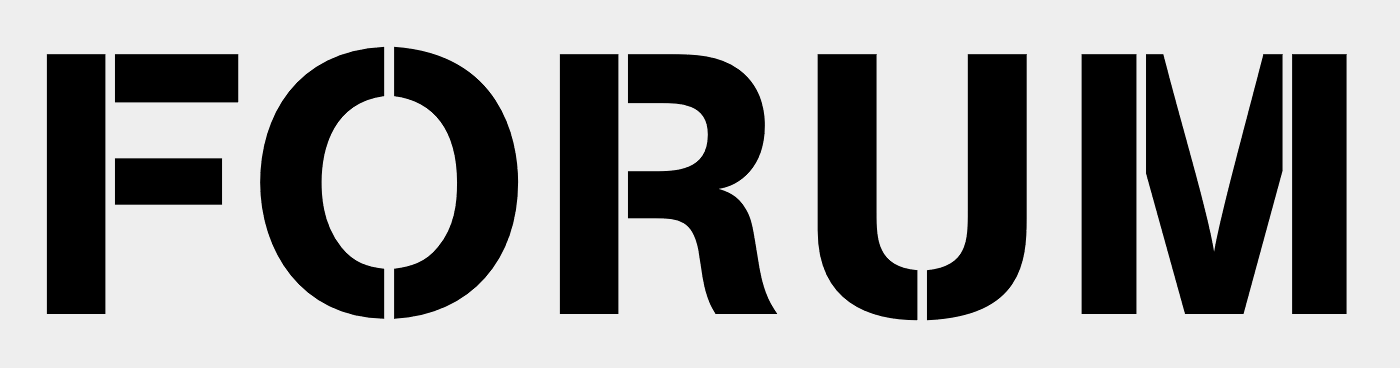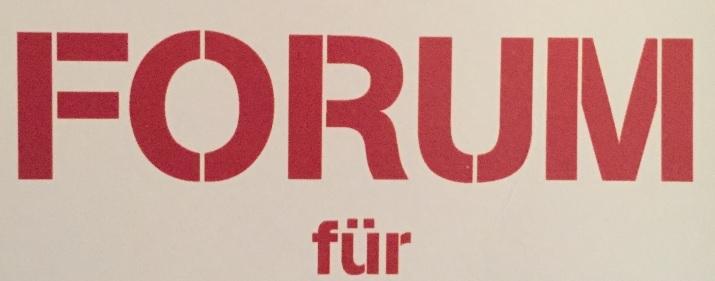
Schriftfont gesucht
Bei dieser Schriftart konnte ich leider nichts finden. Kann da jemand aushelfen ?
Gelöst von Carlito Palm
AG Book Stencil
Helvetica-ähnliche Stencils gibt’s ja einige, aber ich wollte das genau wissen und hab mich auf die Suche nach dem 2014er Programm von FOR EJE gemacht. Bin ja rechtzeitig fündig geworden ;-)